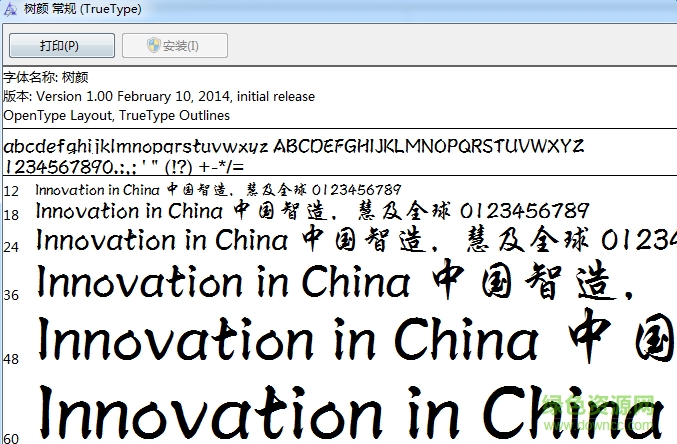
樹顏常規(guī)字體是一款應(yīng)用于設(shè)計方面的簡體中文字體,該字體線條粗細(xì)適中,字形大方得體,整體效果非常出色,并且字庫完整,可用于藝術(shù)設(shè)計、包裝印刷、簽名設(shè)計、圖形設(shè)計等領(lǐng)域,有喜歡的朋友可免費下載收藏。
樹顏常規(guī)字體是一款極具個性的中文字體,該字體形體十分飄逸,瀟灑至極。有喜歡的朋友可以來綠色資源網(wǎng)下載使用!